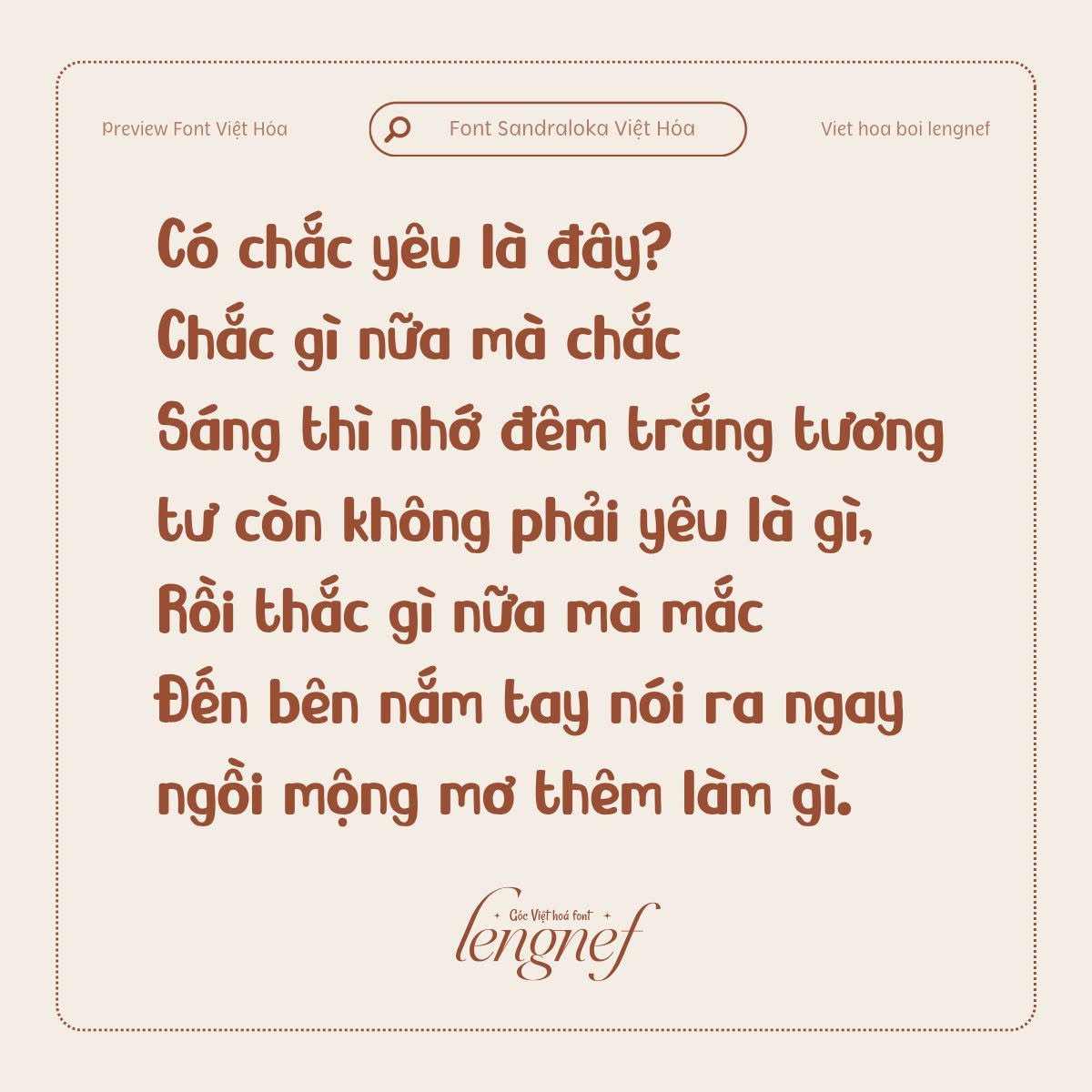
- Tác giả: Modestype Studio
Sandraloka là một phông chữ dễ thương và sống động, được lấy cảm hứng từ bãi biển, mang tinh thần mùa hè và phiêu lưu vào bất kỳ thiết kế nào. Các nét chữ đậm của nó giống như chữ viết tay vui nhộn. Mỗi chữ cái tròn trịa, thân thiện tạo cảm giác thoải mái, lý tưởng cho các thiết kế gợi lên sự vui vẻ, thoải mái, hứng khởi và khám phá.